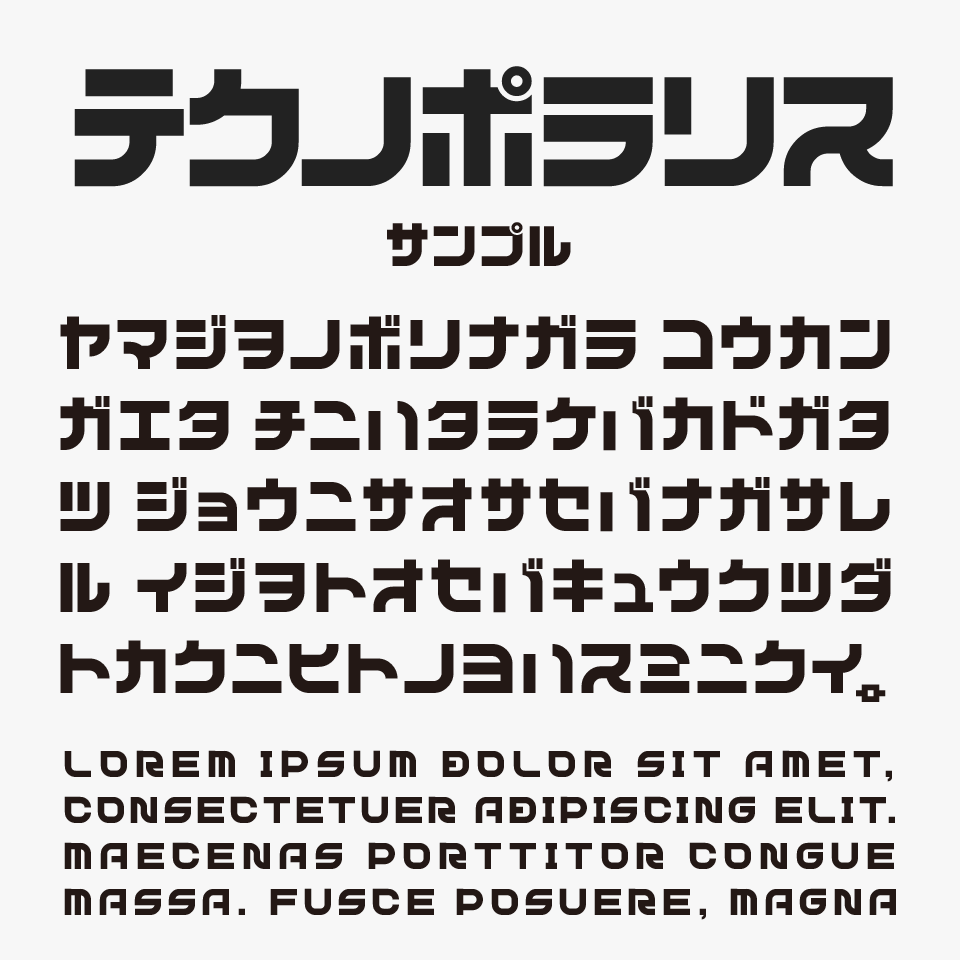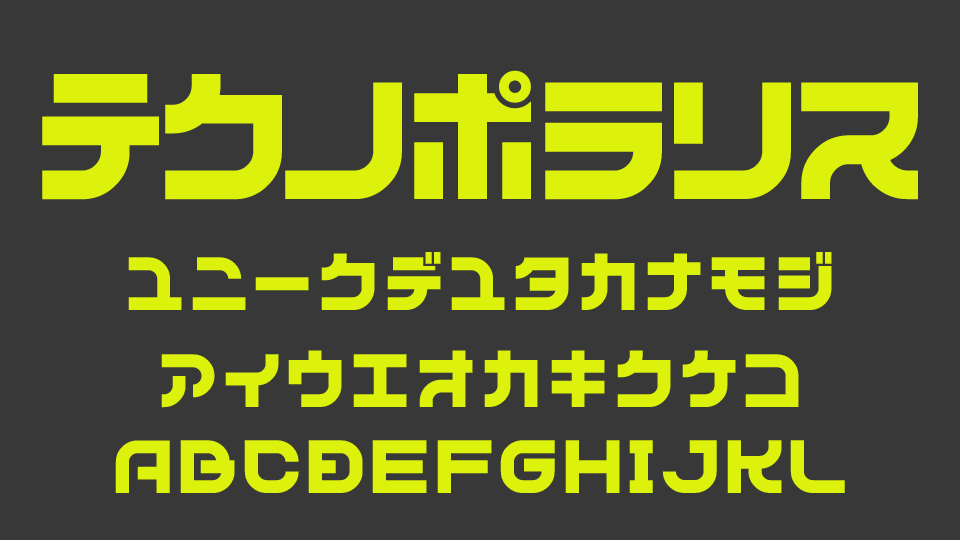
N4テクノポラリスフォントは、太いストロークと鋭角的な字形で構成された、近未来感あふれる極太カタカナフォントです。
線の端や角の処理が非常にシャープで、文字全体がひとつの工業製品のように精緻に設計されているフォントです。
PLUS版(¥ 500)のみの収録ですが、アルファベットもカタカナと同様にすべて大文字の直線的なデザインで統一されており、和文・欧文ともに世界観のブレがなくとってもかっこいい仕上がりとなっているフォントです。